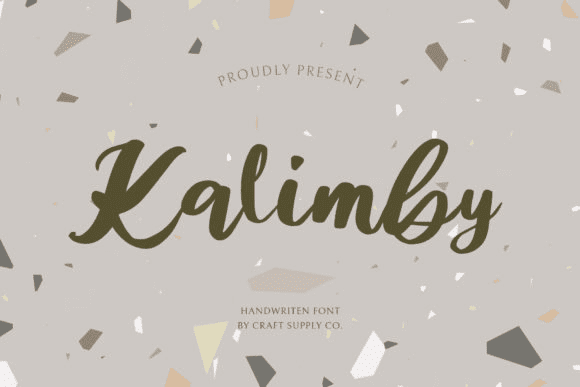
Kalimby - это шикарный, изысканный шрифт, который излучает утонченность и элегантность.
Стильные чередования и лигатуры делают этот шрифт идеальным для любого проекта.